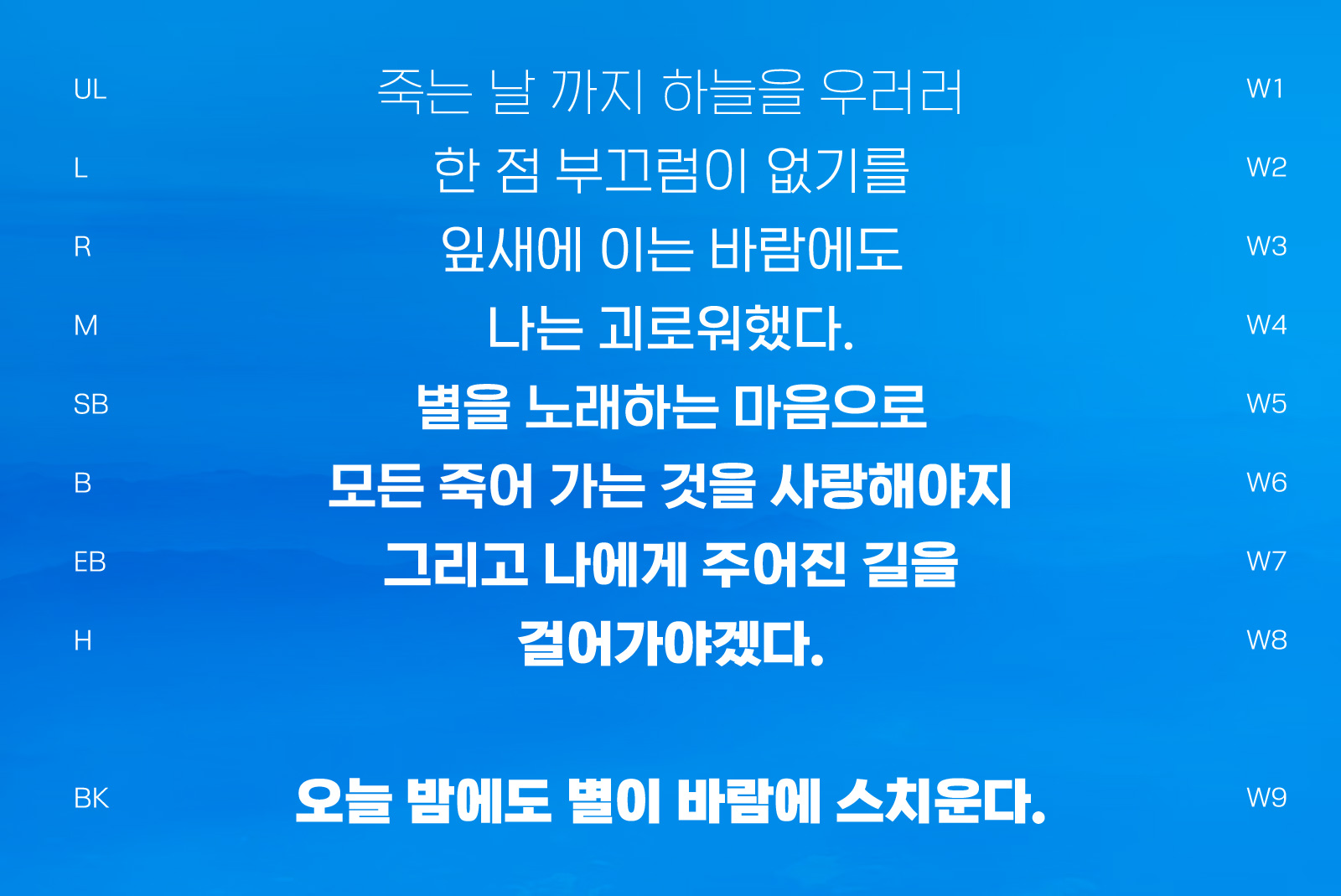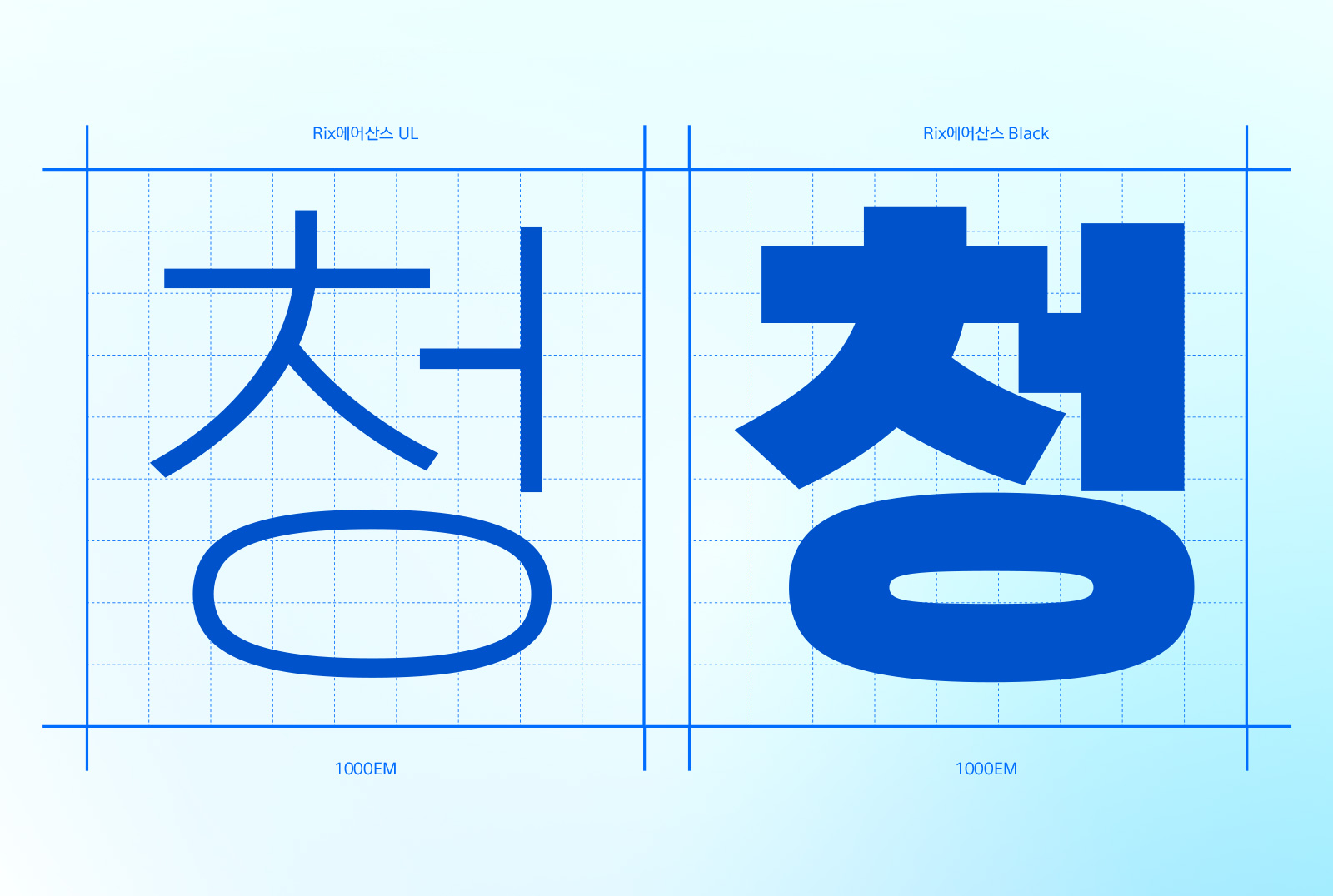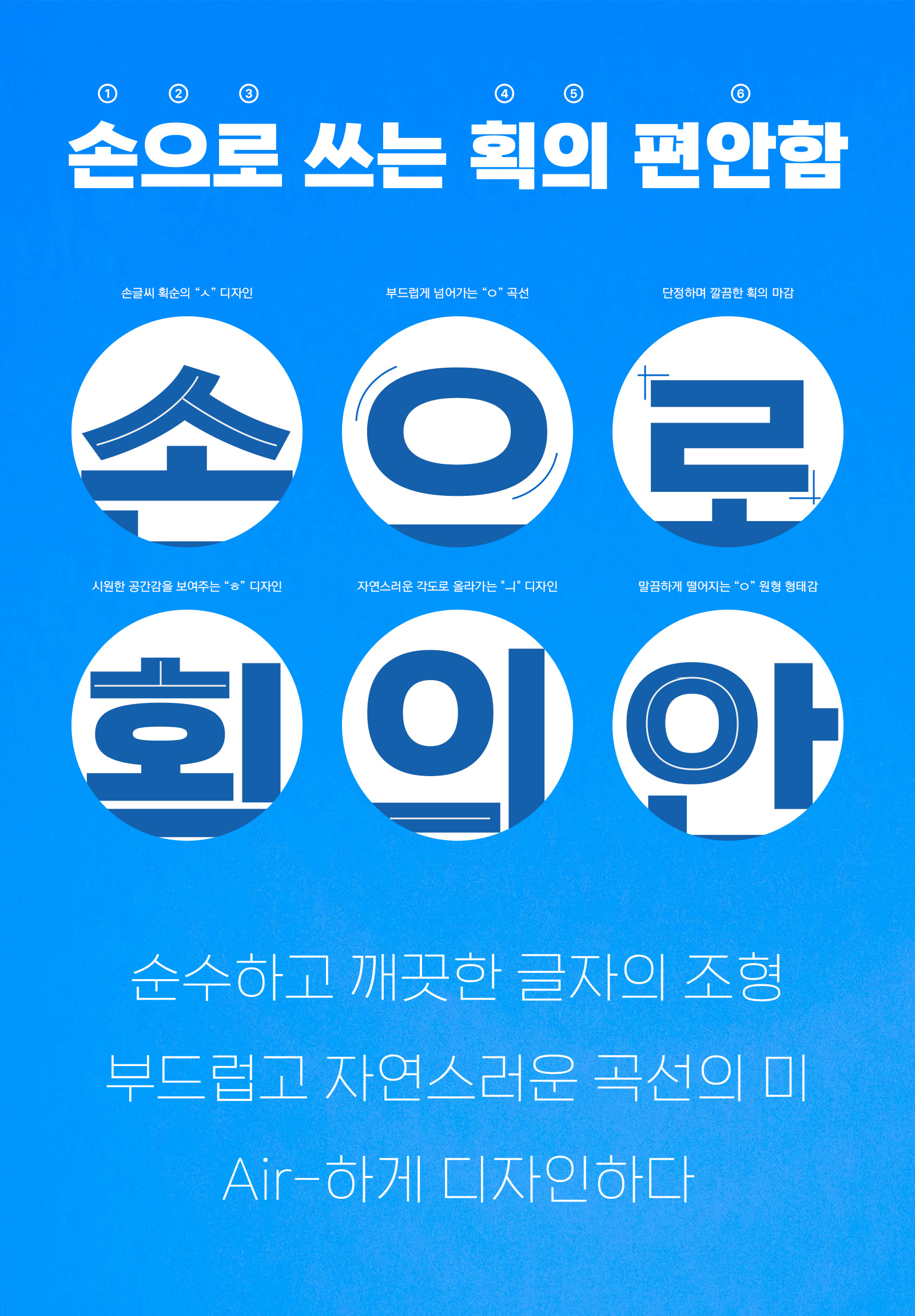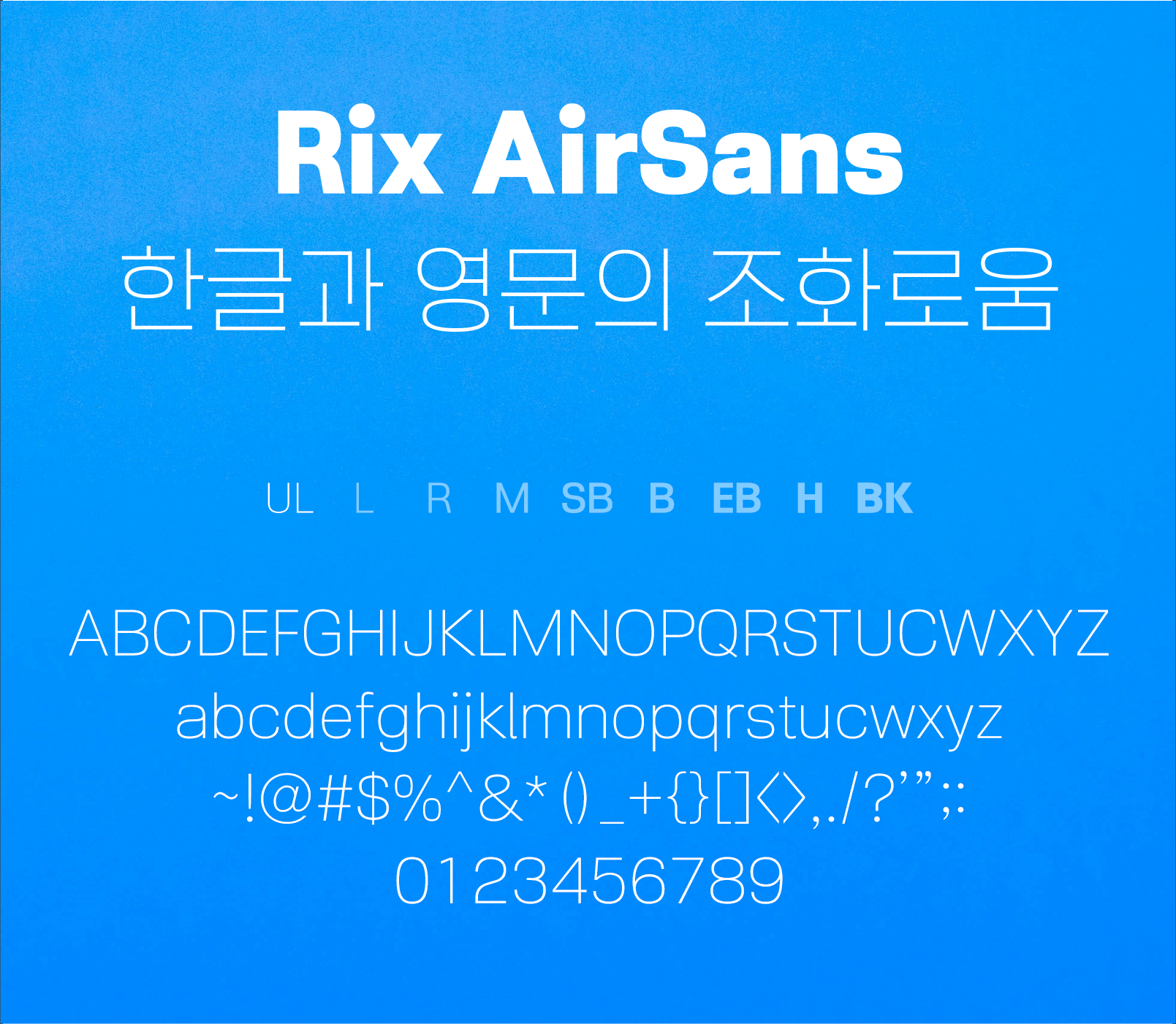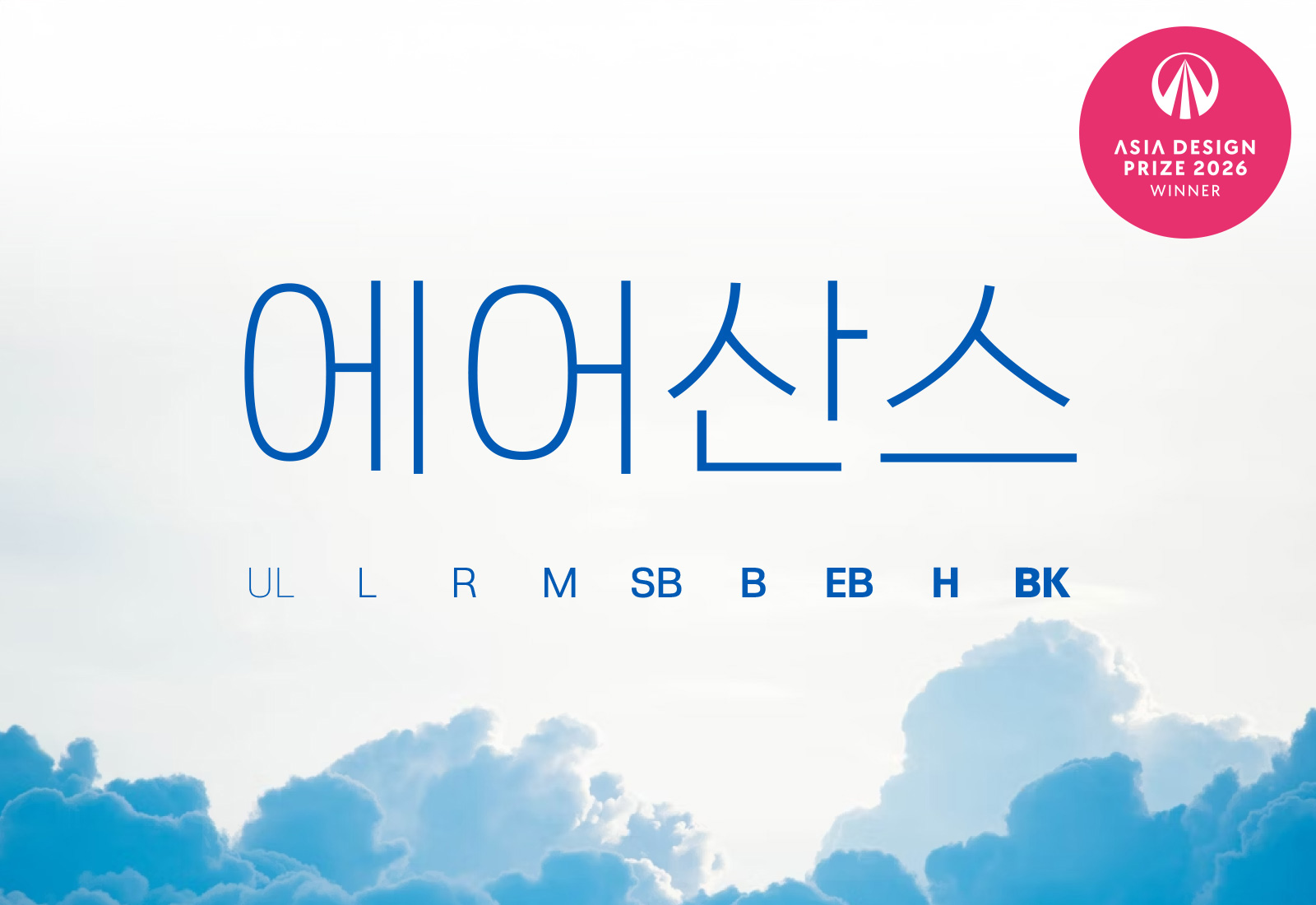
Rix에어산스
9 종 - Black, Heavy, ExtraBold, Bold, SemiBold, Medium, Regular, Light, UltraLight꽉 찬 네모틀의 단단한 골격을 유지하면서, 'ㅅ, ㅇ, ㅈ, ㅊ, ㅎ' 계열 자소에
손글씨 획순에 의한 부드럽고 자연스러운 곡선미를 추가한 서체입니다.
| 폰트디자인 | ㈜폰트릭스 |
| 디자인디렉팅 | 박용락 |
| 폰트구성 | 한글 2,350자 + 추가자 430자 / 한자 4,622자 / 라틴 94자 / 라틴확장 110자 / 약물 986자 + 추가자 69자 |
Rix에어산스는 다양한 굵기로 넓은 선택의 폭을 제공합니다.
꽉찬 형태의 네모꼴로 안정감을 주는 글자의 비례감
휴머니스트 감성이 담긴 자소로 친근한 이미지를 보여주는 글자의 인상
Rix에어산스의 영문 디자인
사용 예시